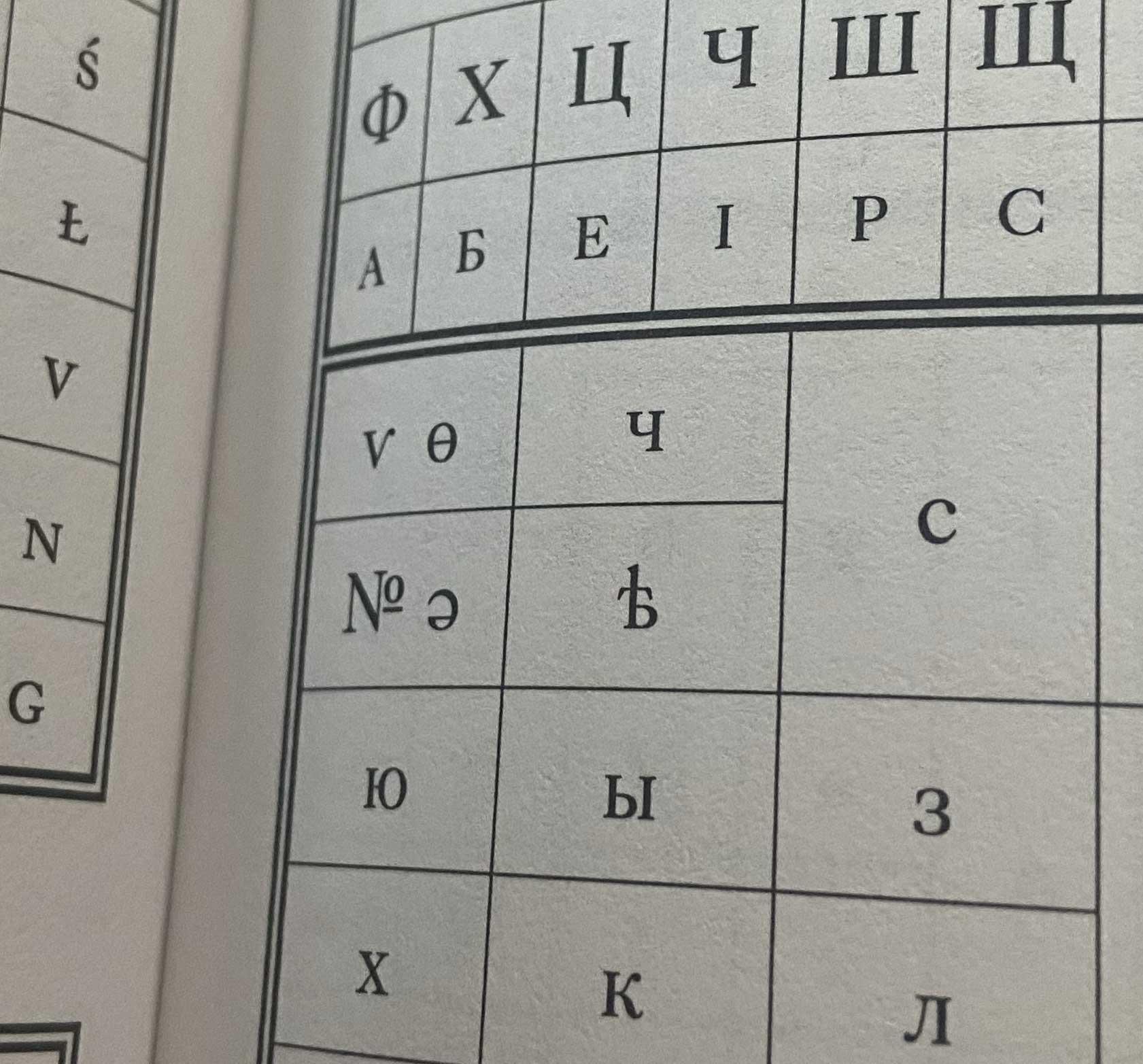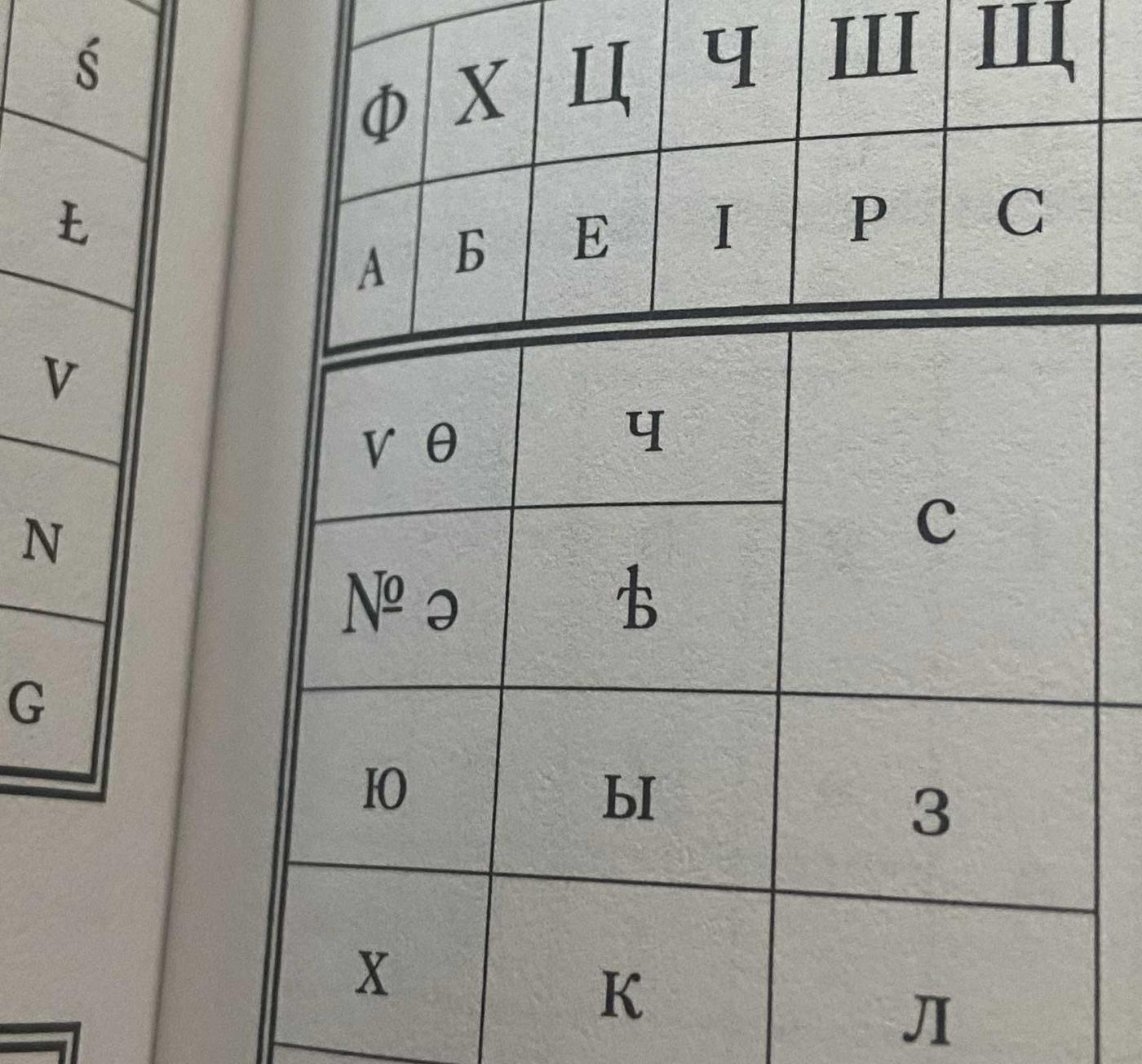
Sonderzeichen im Bleisatz
beim Umsortieren alter Bleisatzschriften von "hässlichen" in "schöne" Setzkästen ist uns gestern ein Sonderzeichen, ein seitenverkehrtes P mit Schnörkel unten (ähnlich dem Sonderzeichen in Quark für "Zeilenende") in die Hände gefallen.
Kann mir jemand sagen, wie dieses Zeichen heisst und wo es im laufenden Satz benutzt wurde?
Im Internet hab ich (wie meist) nichts gefunden.
Wir haben es trotz verschiedener Handys nicht fotografieren können (6-Punkt-Schrift), aber ich denke, ihr wisst, welches Zeichen ich meine...
Auf einen Scanner legen?
das wird einfach sein (Paragraph-Zeichen, wird in der elektr. Textverarbeitung als Zeichen für Zeilenschaltung verwendet).
@Thomas Kunz Ja, das ist es ! So ein schöner Name!
@109Leider gibts auch den nicht (meiner verweigert seit dem letzten Catalina-Update seinen Dienst)
@Ralf Herrmannhabbsch grad gemacht...
@StötznerAlinea heißt das Ding ;-)
Aber jetzt nochmal die Frage: wofür wurde das Zeichen früher im Setzkasten gebraucht ?
Ah jetzt – ja... :-D
ich habs im Link von Thomas gefunden und werd den Artikel für die Museumssetzer ausdrucken. Ihr wart wie immer sehr hilfreich – DANKE !
Der Titel dieses Threads paßt so hervorragend. Ich suche eine Bleisatzschrift, in 8 oder 10 pt., die das Sonderzeichen »№« enthält. Mein Favorit ist eine Fraktur muß aber nicht.
Willst Du eine Bleisatzschrift kaufen oder was ist unter "suchen" zu verstehen?
Dieses Sonderzeichen ist m.E. sehr selten in irgendwelchen Schriften enthalten und mir bisher tatsächlich nur als Sonderzeichen oder (komischerweise) in kyrillischen Schriftsätzen über den Weg gelaufen.
Ja ich würde die Schrift wenn Sie das Sonderzeichen enthält und mir gefällt auch kaufen.
Ich habe auch ein wenig recherchiert und Du hast recht anscheinend gibt es dieses Sonderzeichnen nur bei mathematischen Zeichensätzen oder wurde separat angeboten. Leider sehr selten.
Das Numero-Zeichen ist in der Tat fester Bestandteil der kyrillischen Zeichensätze, egal ob Buchdruck, Schreibmaschinen oder Computer-Tastaturen.
Die Idee, nach einer kyrillischen Schrift Ausschau zu halten, ist also gar nicht so verkehrt.
Gibt es Erkenntnisse warum das so ist?
Wenn Du nur das Zeichen suchst (welches auch in kyrillischen Sätzen nicht gerade zahlreich vertreten ist, was den Kauf eines ganzen Satzes nur deshalb etwas skurril wirken lässt): versuch doch es noch einzeln gießen zu lassen, solange Gerstenberg noch arbeitet. Oder frag mal bei den letzten noch tätigen Monotypeleuten nach ob die das Zeichen haben und gießen können.
ChatGPT hat Erkenntnisse. Bewerten kann ich sie nicht ;-)
Das Zeichen №, das häufig in der russischen Sprache verwendet wird, stammt ursprünglich aus dem Lateinischen und wird auch in anderen Sprachen wie Englisch, Französisch und Deutsch verwendet. Es handelt sich dabei um eine Abkürzung für das Wort "Nummer" und dient dazu, Nummern oder Kennzeichnungen zu kennzeichnen.
Obwohl das lateinische Zeichen N nicht in der russischen Schrift enthalten ist, wird das Zeichen № in der russischen Sprache dennoch verwendet. Dies liegt daran, dass die russische Sprache viele Fremdwörter aus anderen Sprachen übernommen hat, die das Zeichen № verwenden. Es wurde zu einem festen Bestandteil der russischen Schriftsprache, insbesondere in offiziellen Dokumenten, Publikationen und allgemeinem Schriftverkehr.